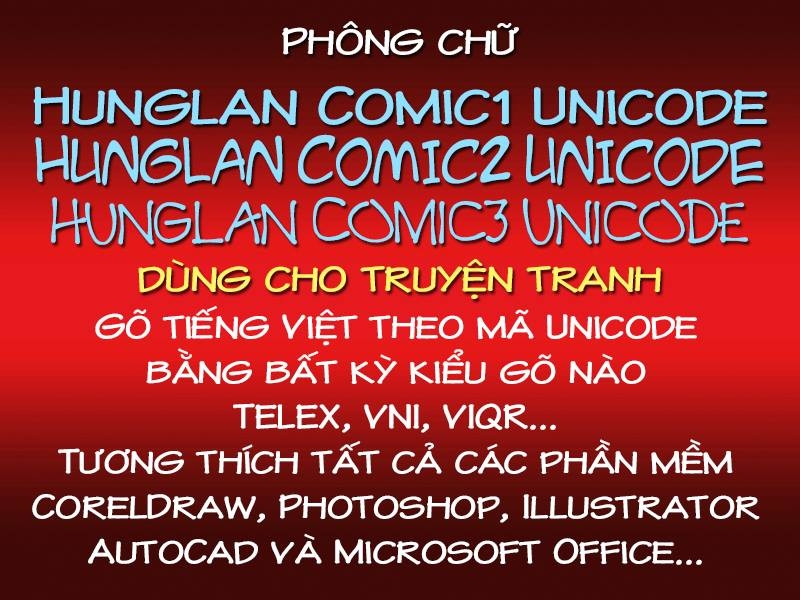
Chia sẻ bộ font chuyên dùng làm lời thoại cho truyện tranh của anh Lân Hùng
Vì thấy một số truyện tranh của các tác giả trẻ dùng font do mình sáng tác để làm lời thoại nhưng có bất tiện là không phải mã Unicode nên anh Nguyễn Lân Hùng đã quyết định thiết kế lại bộ font này bằng bộ mã thông dụng hơn và chia sẻ nó. Các bạn có thể tải về bộ font này theo địa chỉ: http://hunglan.com/share/hlcomicuni.rar hoặchttps://tenlua.vn/download/0037e62ee70d6a0f1c30/hlcomicuni, hoặc https://app.box.com/s/04nc6u8mvwgcfko475bphr70vjobfhvi